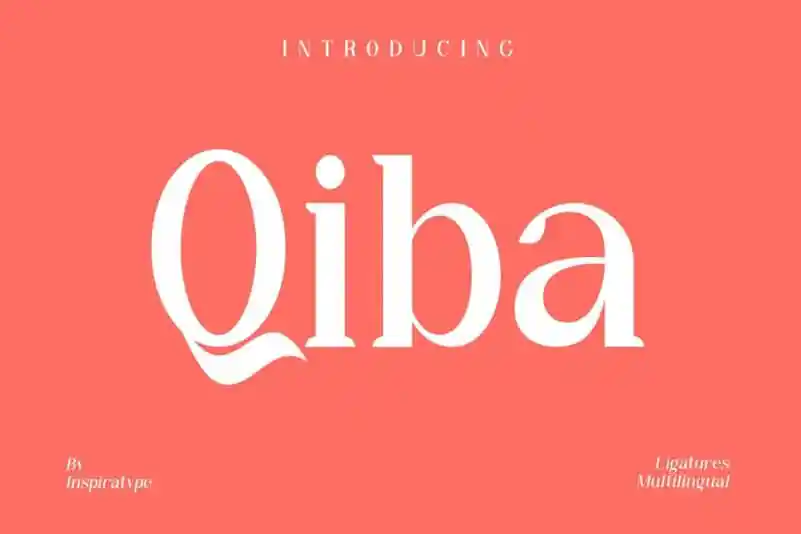
A Qiba Serif Font é uma elegante escolha para projetos que valorizam estilos minimalistas e sofisticados. Ela oferece dois tipos de fontes recomendadas para design minimalista, apresentando um contraste moderado entre os traços. Inspiratype cuidadosamente concebeu a Qiba, inspirada nas clássicas posters, fazendo-a parecer como se fosse impressa à mão. A fonte contém todas as letras maiúsculas e minúsculas, números e pontuações, além de uma infinidade de variações em cada caractere, incluindo alternativas do OpenType, ligaturas comuns e até mesmo swashes adicionais para permitir que você personalize seus designs de acordo. É perfeita tanto para uso em logotipos quanto em letras de carta, posters, roupas, etiquetas ou qualquer outro tipo de projeto.